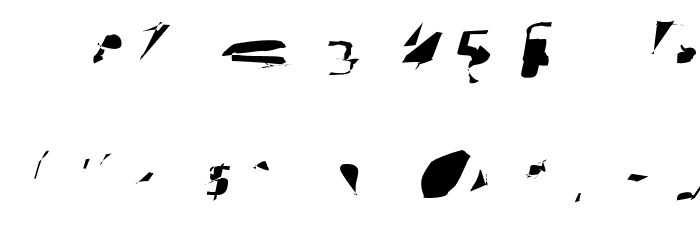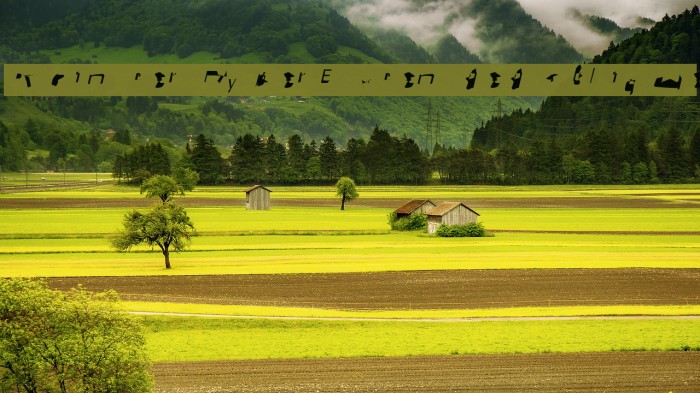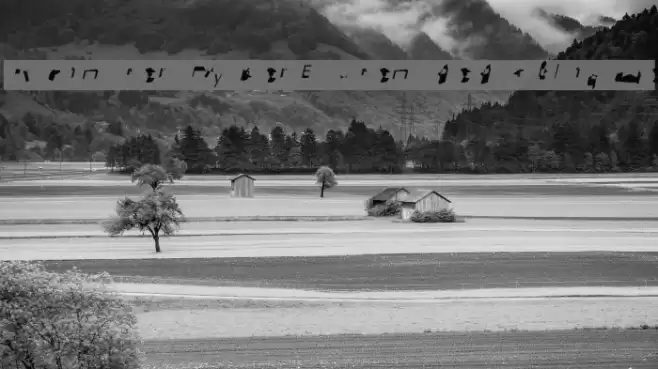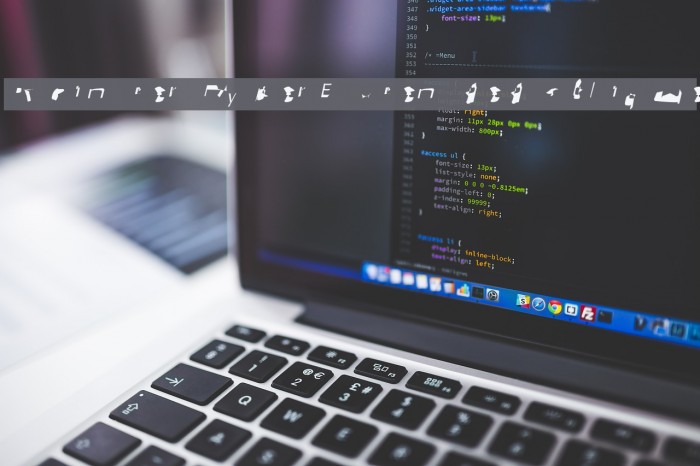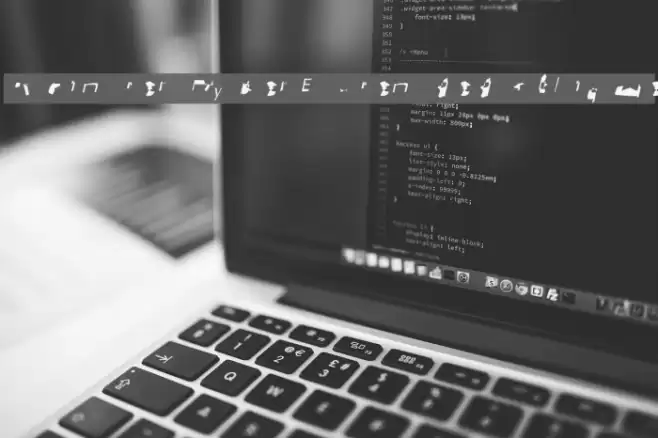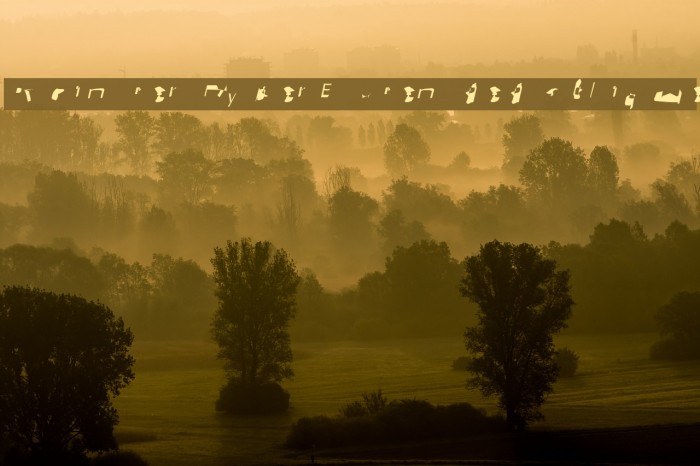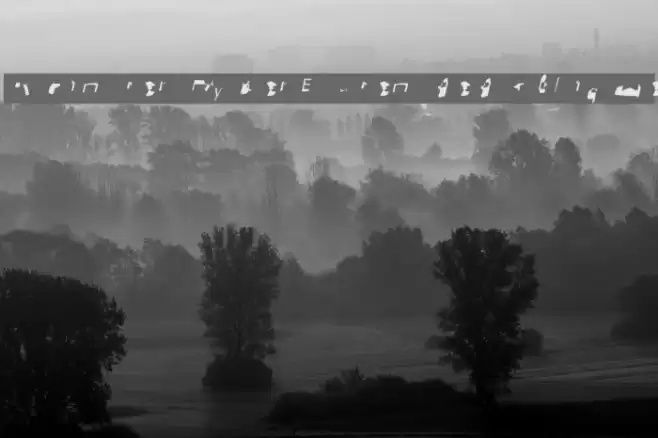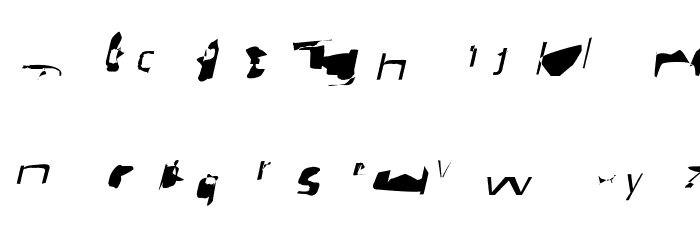
Pointer HyperExtended Oblique Font
✎ Distorted Eroded
| Style général | Modern, Abstract |
| Cas d'utilisation | Logos, Posters, Artistic Designs |
| Projets proposés | Ideal for experimental art projects, avant-garde posters, and edgy graphic designs. |